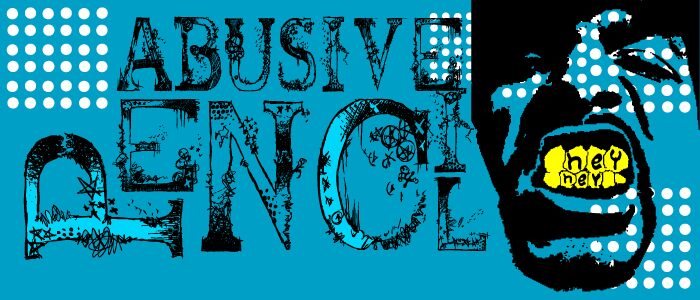
Abusive Pencil ist eine kostenlose, handgezeichnete Display-Schrift, die vom Look eingeritzter, abgenutzter Bleistiftbuchstaben inspiriert ist. Die Buchstaben wirken kratzig und schelmisch, mit rauen Kanten, kleinen, splitterartigen Einkerbungen und verstreuten sternförmigen Markierungen. Das lässt die Großbuchstaben eher wie Kritzeleien aus einem Schulheft erscheinen als wie ein ordentliches Schild.
Damit findet diese kostenlose Schrift ihren natürlichen Platz auf Plakatüberschriften, in Zines, bei Notizbuch-Designs, auf Party-Flyern und in spooky oder verspielten Verpackungen, bei denen ein zu glattes Finish einfach nicht passen würde. Sie eignet sich außerdem hervorragend für kurze Schlagzeilen, Kapitelanfänge und Monogramme, da die Textur der Bleistiftstriche schon bei wenigen Buchstaben ihre volle Wirkung entfaltet.